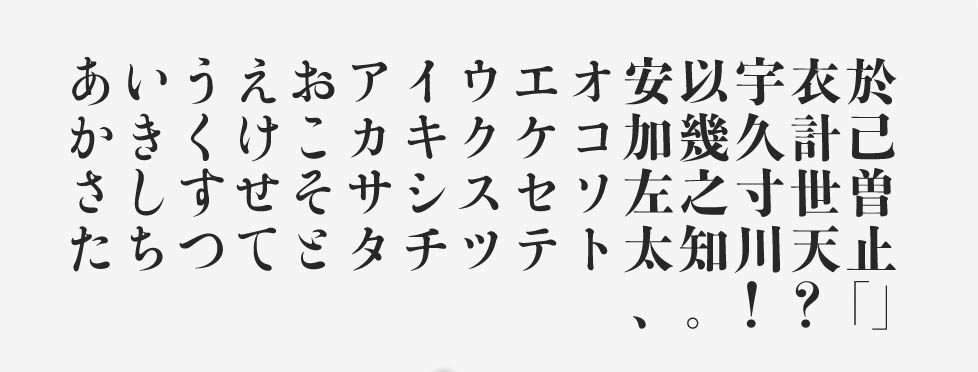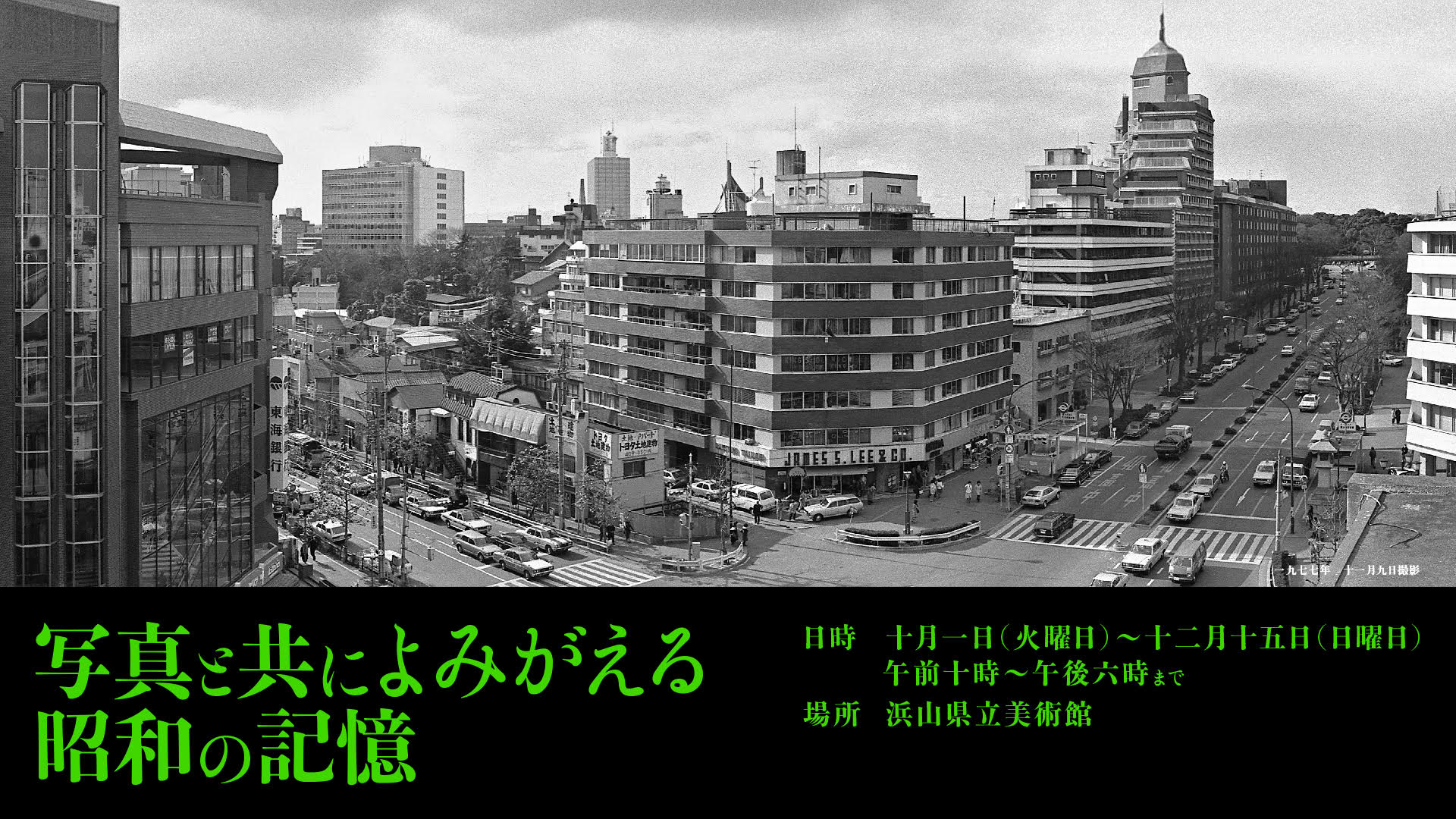
「游築見出し明朝体」について
游築見出し明朝体は、大正時代の東京築地活版製造所36ポイント明朝活字をベースとして開発されたフォントです。見出し用の書体として大きなサイズでも使えるように、文字の形そのものに魅力を持たせることを重視して設計されています。元の文字を最大限に生かし、太さや字面や傾きなどの個性もあえて残しながらフォント化されました。
「游築見出し明朝体」の特徴
書籍のタイトルや見出しなどに適しています。明朝体の中でも横画がかなり細めにデザインされているのは、大きな級数で太く見えないようにするための処理です。ハライの先端もやや細めで、全体的にふところは狭めに絞られています。
特徴的な仕様として、英数字は収録されていません。これは、積極的に混植を行うデザイナーたちの志向を汲んだためです。また、別途に異体字のみを搭載した游築見出し明朝体 Altというフォントが用意されています。
制作デザイナーの解説コメント
フォント名に「見出し」と付いていますが、今回の作例程度のサイズ感であれば、見出し以外にも問題なく使って良いと思います。長文を組むには不向きかもしれません。大きめのサイズの文字を、キツメに組んであげると特に映えるフォントですね。
- よく使われるシーン
書籍、雑誌、看板、ポスター